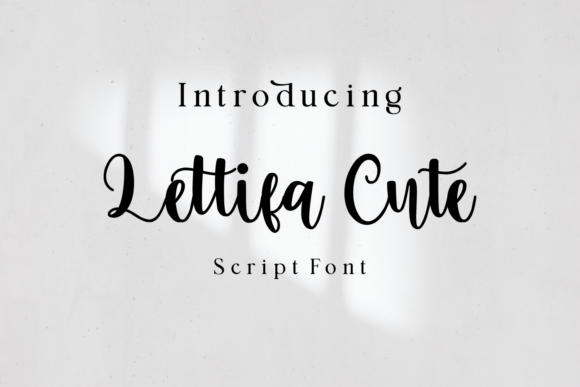
Lettifa Cute
Encontrar los elementos de diseño adecuados puede ser un desafío, pero Lettifa Cute ofrece una colección excepcional que eleva tu trabajo al instante.
Elaborado con precisión, Lettifa Cute proporciona vectores limpios, tipografía suave y una licencia comercial para tu tranquilidad.
Ya sea que estés creando productos POD (impresión bajo demanda), invitaciones de boda o gráficos para redes sociales, Lettifa Cute es una opción ideal.